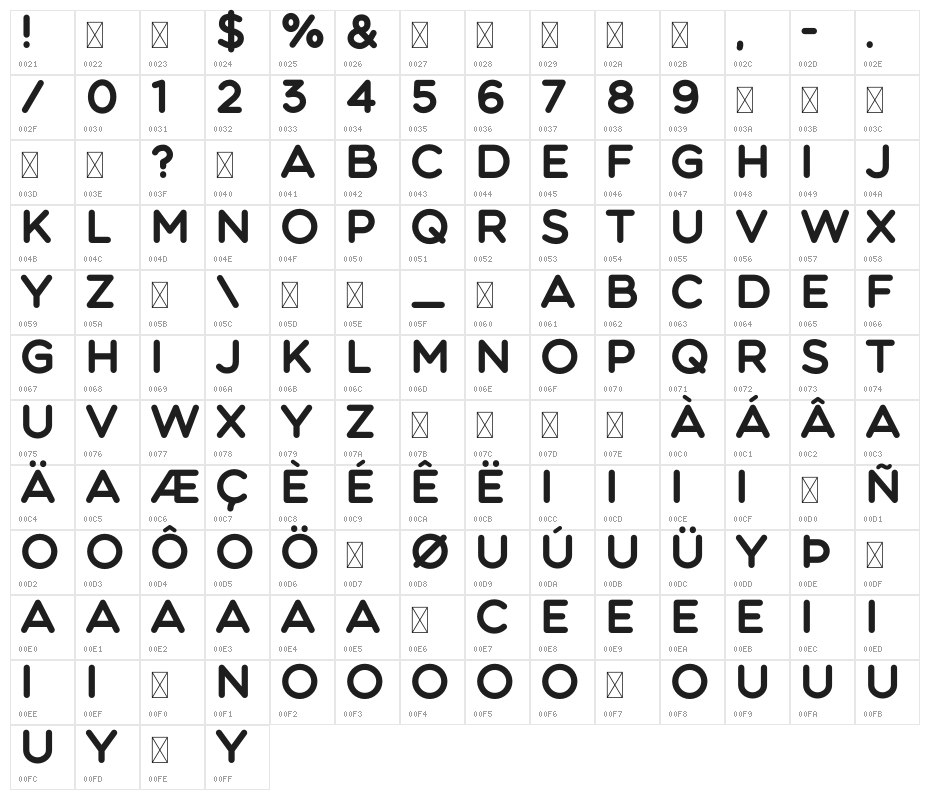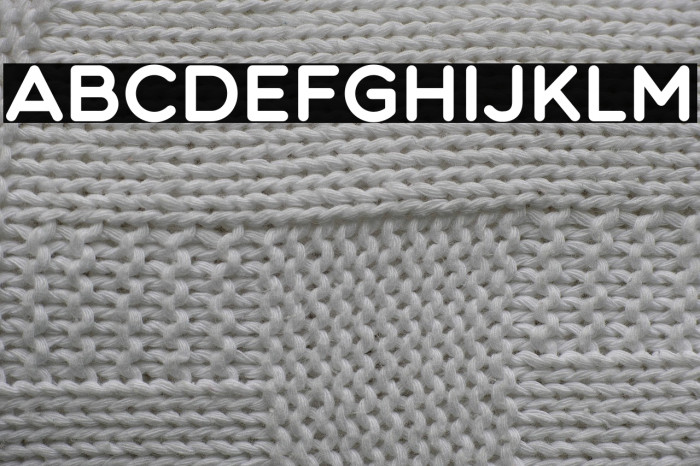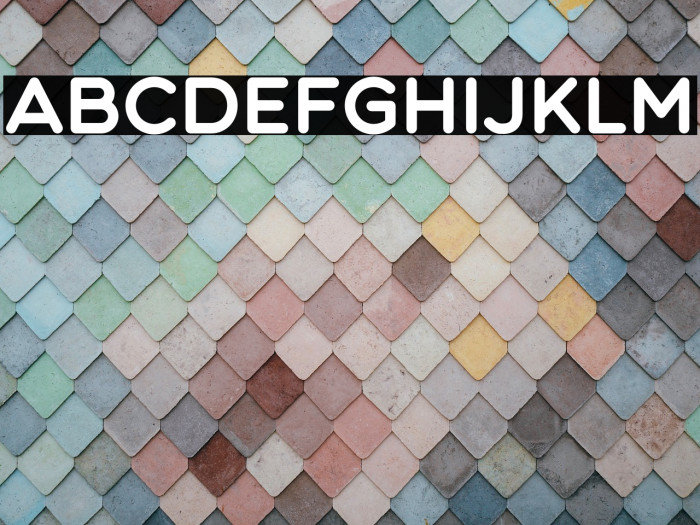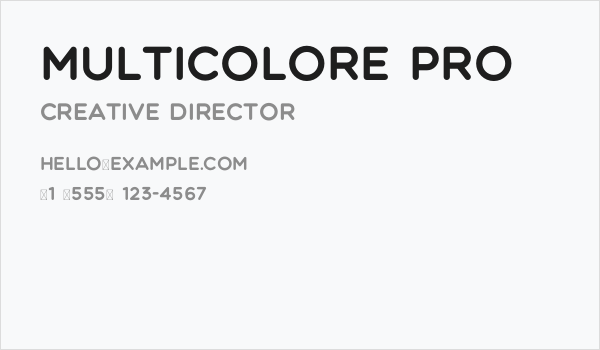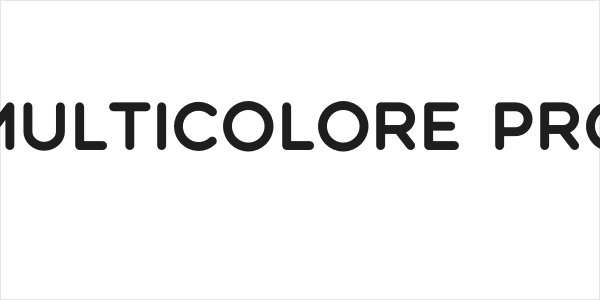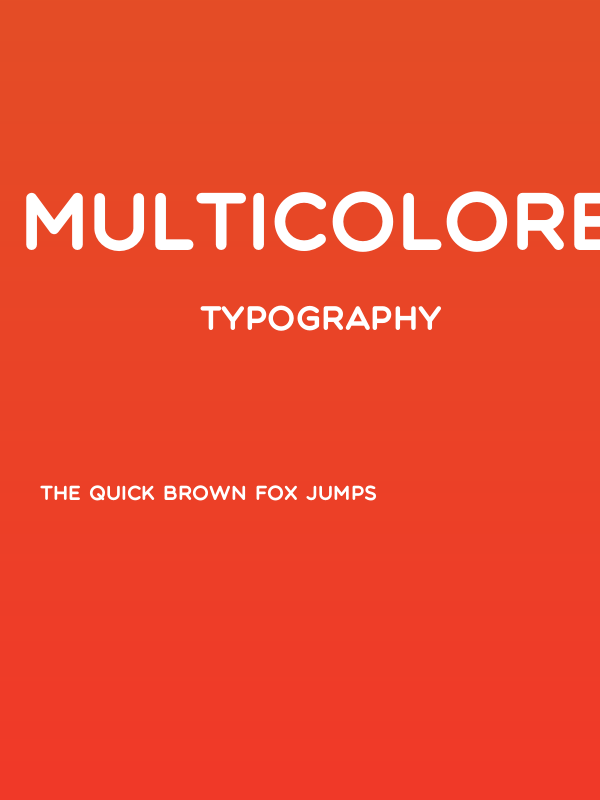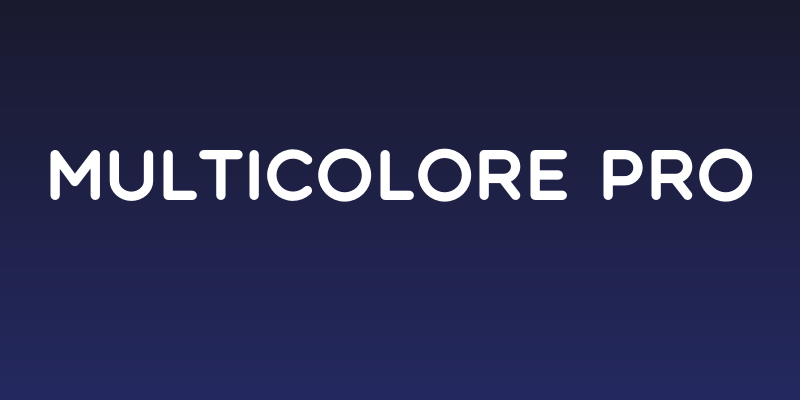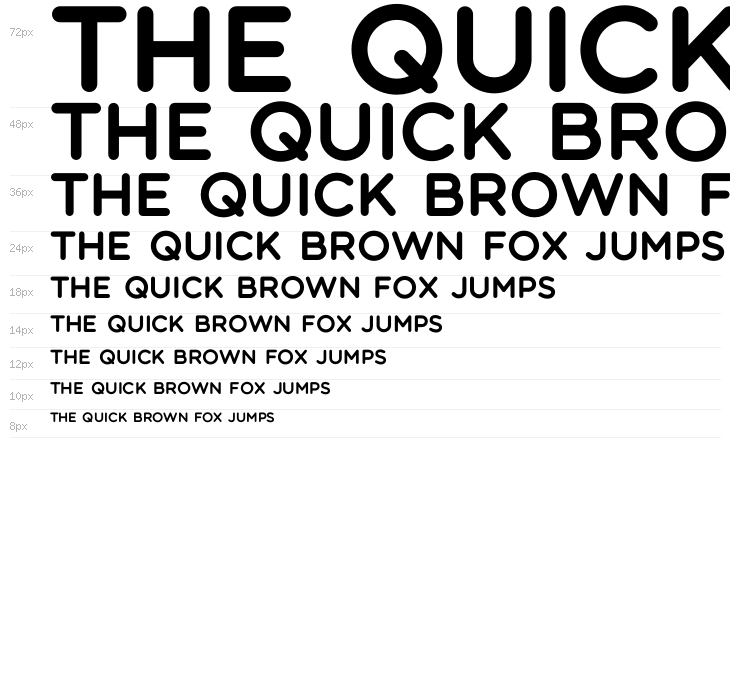
Multicolore Pro Font
✎ Sans Serif
| Anwendungsfall | Headlines, Body text, Logos |
| Vorgeschlagene Projekte | Ideal for branding, web design, advertising, and user interfaces due to its clean and modern appearance. |